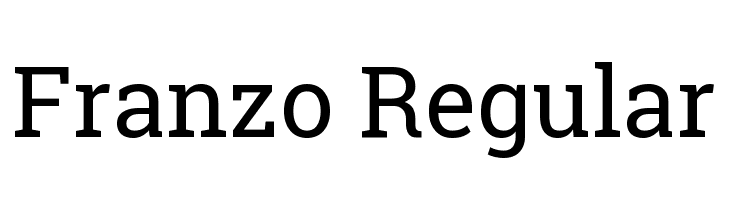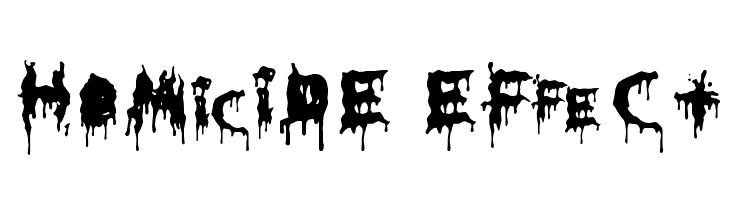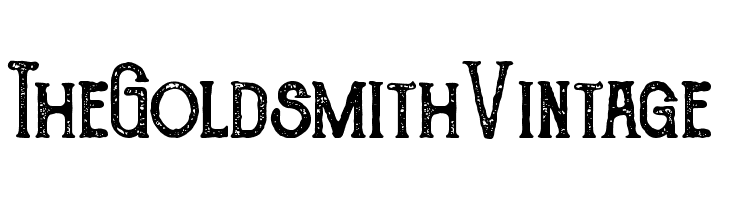
Bienvenue dans Polices Populaires — là où se rencontrent popularité et qualité. Voici les polices les plus téléchargées et utilisées cette année. Pour des choix sûrs (logos, web, social), commencez ici.
Chaque police phare se distingue par équilibre, lisibilité et polyvalence. Vous trouverez des sans‑serifs modernes, des scripts élégantes, des serifs vintage et des displays minimalistes.
A playful, bold font with a hand-drawn, whimsical style.
A modern, semi-bold, italic sans-serif font with a clean and dynamic style.
Elegant serif font with medium weight and italic style.
A bold, decorative font with a striped gradient effect.
An abstract, graffiti-like font with bold, irregular shapes.
A playful, handwritten font with smooth curves and a casual style.
A classic serif font with elegant, decorative elements and modern touches.
A bold, futuristic font with sharp, angular edges and a geometric design.
A bold, expanded font with geometric shapes and minimal contrast.
A playful and artistic handwritten font with fluid strokes and dynamic style.
A bold, 3D geometric font with a futuristic and dynamic style.
A modern, clean font with consistent stroke thickness and balanced spacing.
A bold, geometric font with an industrial and modern design.
A modern, bold, italic sans-serif font with expanded width and medium contrast.
A classic serif font with elegant curves and medium contrast, ideal for sophisticated design projects.
An elegant cursive script font with flowing, connected letters.
A bold, playful font with whimsical, hand-drawn characteristics.
An elegant script font with flowing, cursive style and high contrast strokes.
A futuristic, geometric font with sharp angles and a tech-inspired design.
A rugged, hand-drawn style font with an ancient, textured appearance.
A sleek, modern font with elongated, narrow characters and minimal contrast.
A playful, handwritten-style font with bold, smooth strokes and a casual vibe.